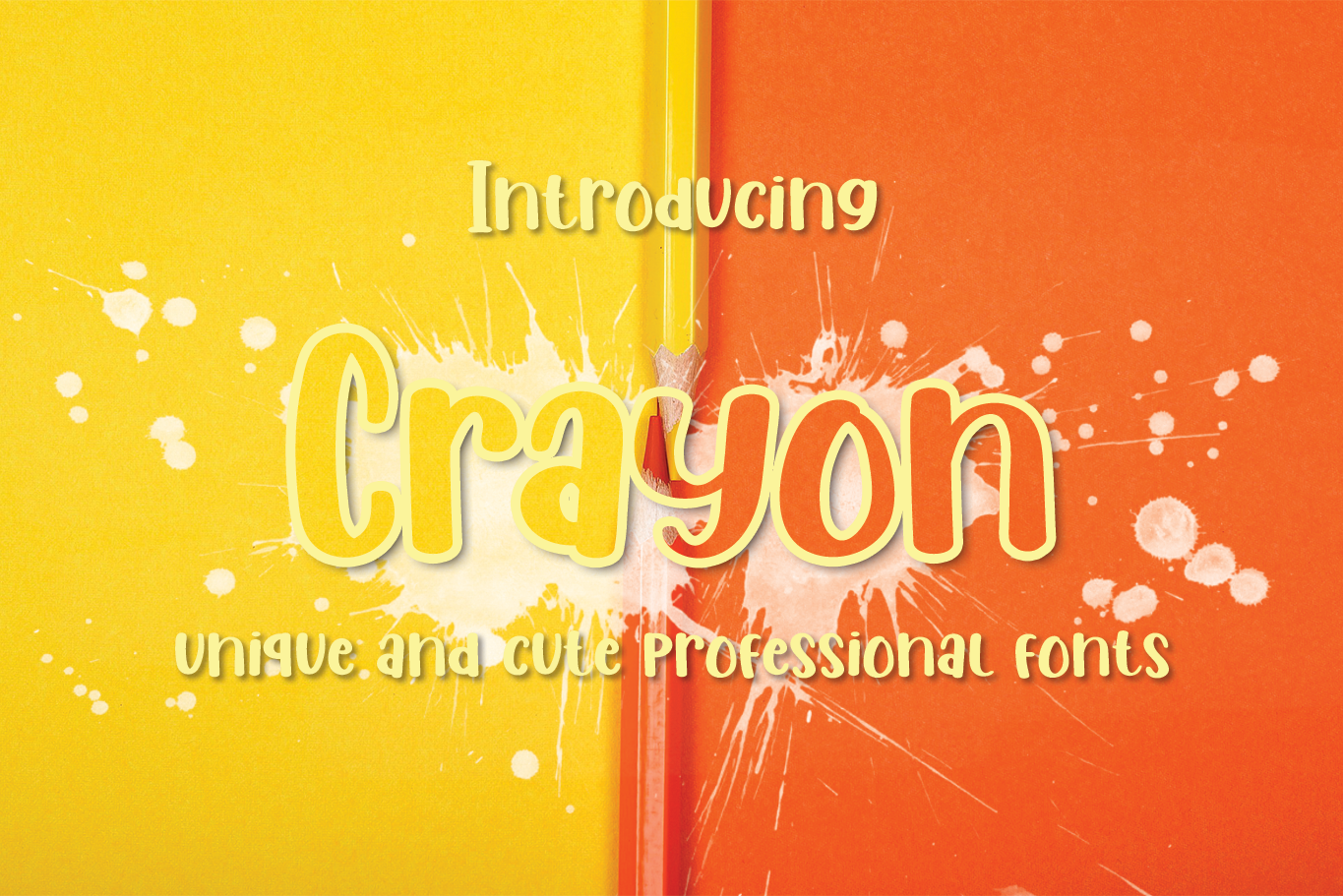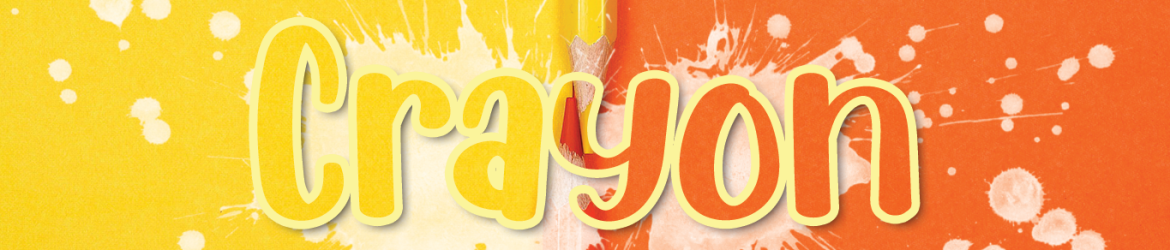
A Crayon Font é uma escolha perfeita para aqueles que desejam adicionar um toque divertido e relaxado aos seus projetos digitais. Esta tipografia do tipo de exibição, criada pelo Erik Studio, se destaca como uma opção ideal tanto para designs relacionados a histórias infantis quanto para jogos infantis. Suavemente peculiar e descontraída, ela traz um toque animado que torna qualquer projeto mais agradável ao olhar. Seja você um designer de games para crianças ou simplesmente alguém que busca adicionar uma pitada de diversão aos seus trabalhos, esta fonte oferece uma solução perfeita para quem procura alegria na escrita e design digital. A Crayon Font é uma escolha inteligente para quem deseja incorporar elementos infantis sem abrir mão da estética elegante e sofisticada que o tipo do display pode trazer à sua produção.